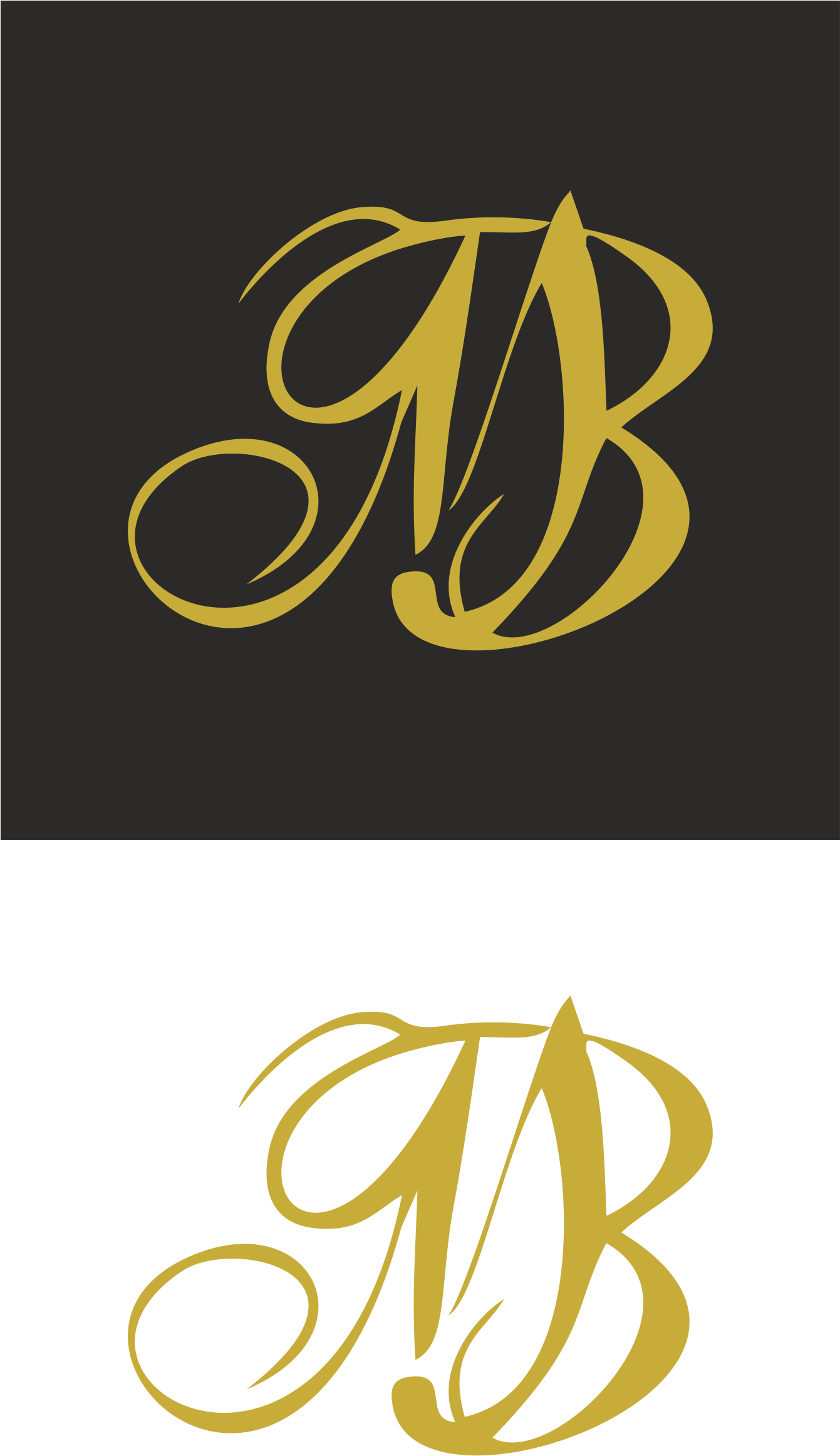
Yazı tipi bulma.
Aşağıdaki M B harflerinin yazı karakteri nasıl bulabilirim?
Yada bu M B harflerini yüksek çözünürlük nasıl yapılabilir ?
Vektörel:
Çizime benziyor internete baktım fakat bulamadım.
Font degil. Font ile.oynanmis
Net halini istiyorsan vektorel cizilmesi lazim
Evet yazı fontuyla oynanmış acelesi yoksa yarın halledelim inşallah
Vektörel: